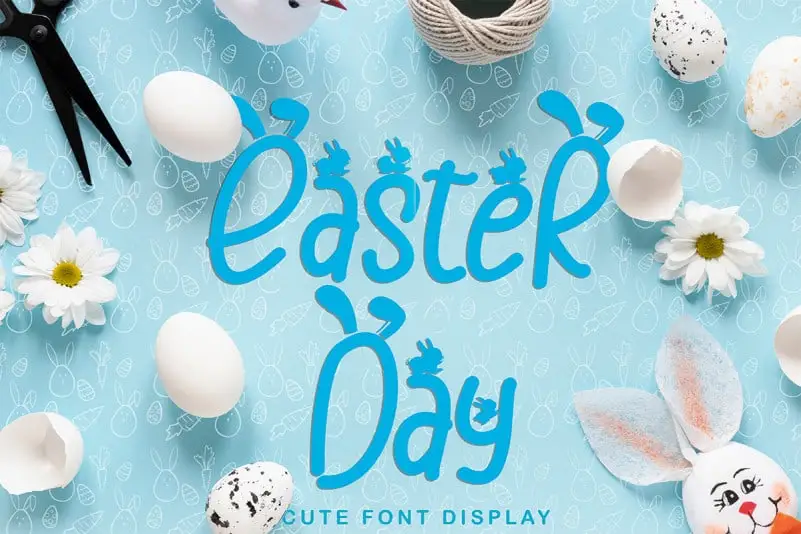
Easter Day Display Font – Download Grátis
A fonte Easter Day Display é uma elegante escolha para qualquer projeto que esteja buscando algo único e divertido. Embalada com um desenho de coelhinho, essa font traz à tona um toque adorável e alegre. Foi projetada especialmente para tornar o uso fácil, permitindo ao designer destacar sem esforço a simplicidade encantadora das letras. Perfeita tanto para comemorações de Páscoa quanto para logomarcas, marca personalizada, banners, títulos de livros e filmes, animações, entre outros projetos destinados aos pequenos e mais jovens, esta font se destaca como uma opção divertida e criativa. Através dela, é possível criar designs que cativam os olhos ao mesmo tempo em que refletem o espírito de Páscoa.